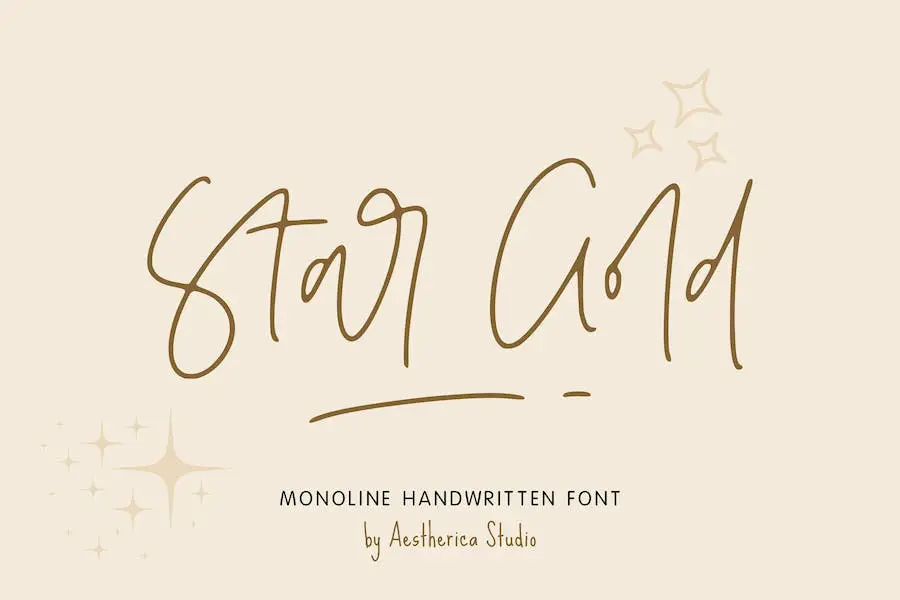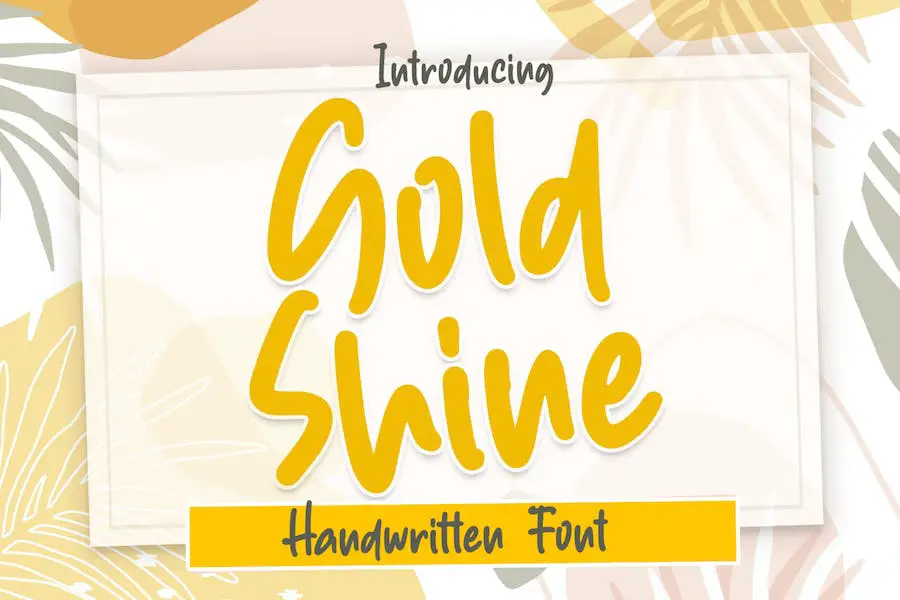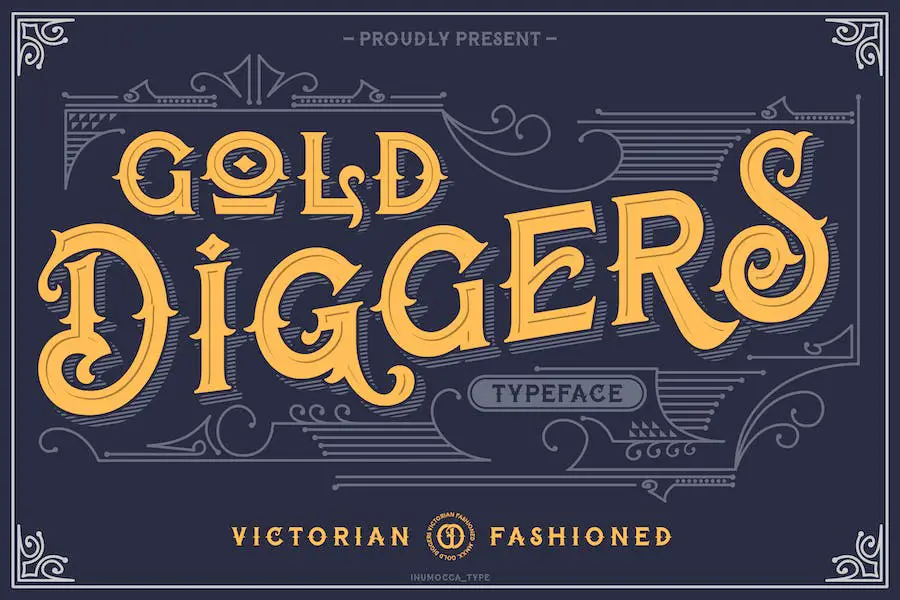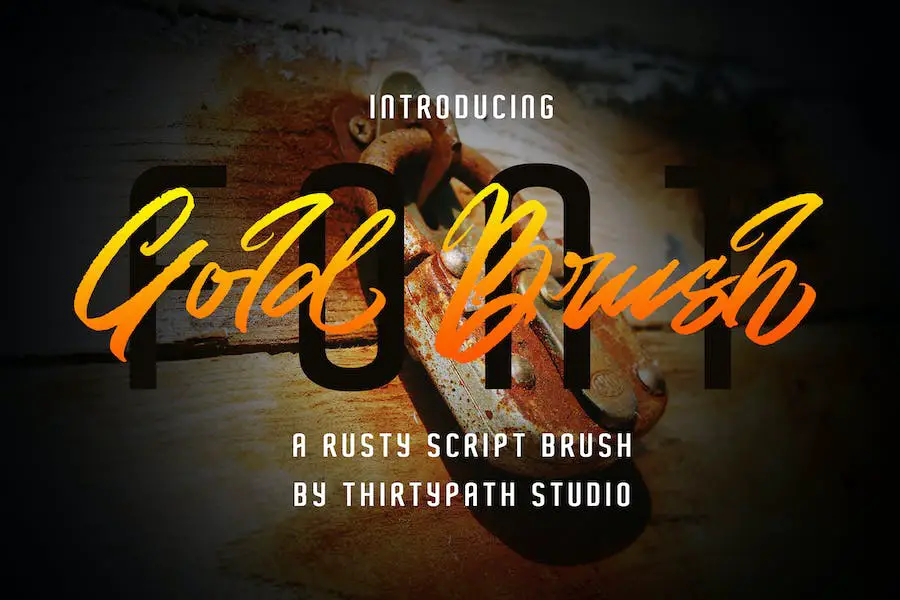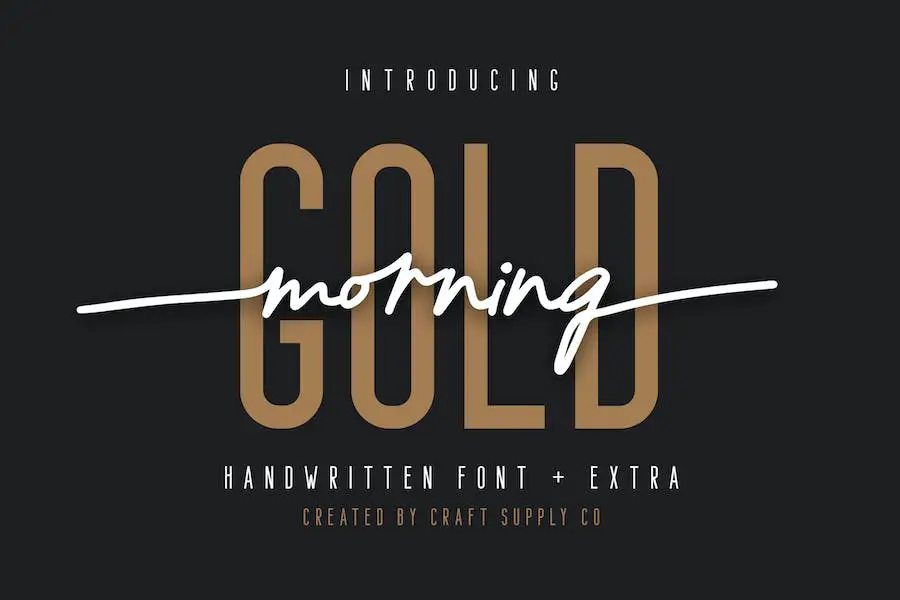
15 En İyi Altın Yazı Tipi 2023 (Ücretsiz ve Premium)
Yayınlanan: 2023-07-23Merhaba, sevgili grafik tasarımcılar! Projelerinizin tasarımını yükseltmek için mükemmel altın yazı tipinin peşinde misiniz? Doğru yere geldiniz. Bu blog gönderisinde, altın yazı tiplerinin dünyasına dalacağız ve size oradaki en iyi 15 yazı tipini sunacağız.
Şimdi, merak ediyor olabilirsiniz, neden altın yazı tipleri? Pekala, sana söyleyeyim. Altın yazı tipleri, herhangi bir tasarıma anında zarafet, telif hakkı ve incelik katabilir.
İster bir logo, ambalaj, davetiyeler veya hatta sadece bir sosyal medya gönderisi üzerinde çalışıyor olun, altın rengi bir yazı tipi kullanmak projenizi diğerlerinden farklı kılabilir.
Bu yazıda, şu anda trend olan en iyi 15 altın yazı tipini sergilemekle kalmayacak, aynı zamanda size her yazı tipi hakkında bazı ilginç istatistikler ve gerçekler sunacağız.
Bu nedenle, yalnızca görsel olarak çarpıcı olmakla kalmayan, aynı zamanda hedef kitleniz üzerinde kalıcı bir etki yaratmak için tasarlanmış yazı tiplerini keşfetmeye hazır olun. Altın yazı tiplerinin dünyasını birlikte keşfedelim ve keşfedelim!
En İyi Premium Altın Yazı Tipleri
Tasarım projelerinize zarafet ve çekicilik katmak mı istiyorsunuz? En iyi 15 premium altın yazı tipinden oluşan özenle seçilmiş seçkimizden başka bir yere bakmayın. Bu çarpıcı yazı tipleri, tasarımlarınızı bir sonraki seviyeye taşıyacak ve onlara lüks ve göz alıcı bir çekicilik kazandıracak.
Bu olmazsa olmaz altın yazı tipleriyle projelerinizi geliştirme fırsatını kaçırmayın - şimdi onları inceleyin ve tasarım oyununuzu yükseltin!
altın kızlar
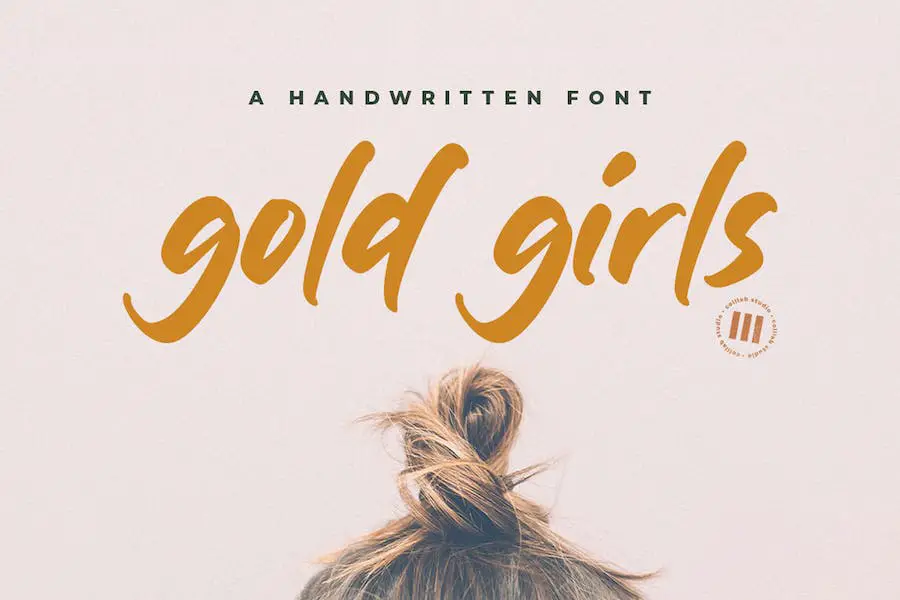
Gold Girls, herhangi bir projeye zarafet ve sofistike bir dokunuş katan süslü bir altın yazı tipidir. Modern yazı stili ve el yapımı kaligrafisi ile trend ve benzersiz bir seçim olarak öne çıkıyor.
Yazı tipi, tasarımlarınıza doğal ve akılda kalıcı bir görünüm kazandıran dekoratif karakterlere ve düzenli bir taban çizgisine sahiptir.
Davetiyeler, logolar veya sosyal medya grafikleri tasarlıyor olun, bu yazı tipi hedef kitlenizi etkileyecek kişiselleştirilmiş ve el yazısı bir dokunuş katacaktır.
saylena
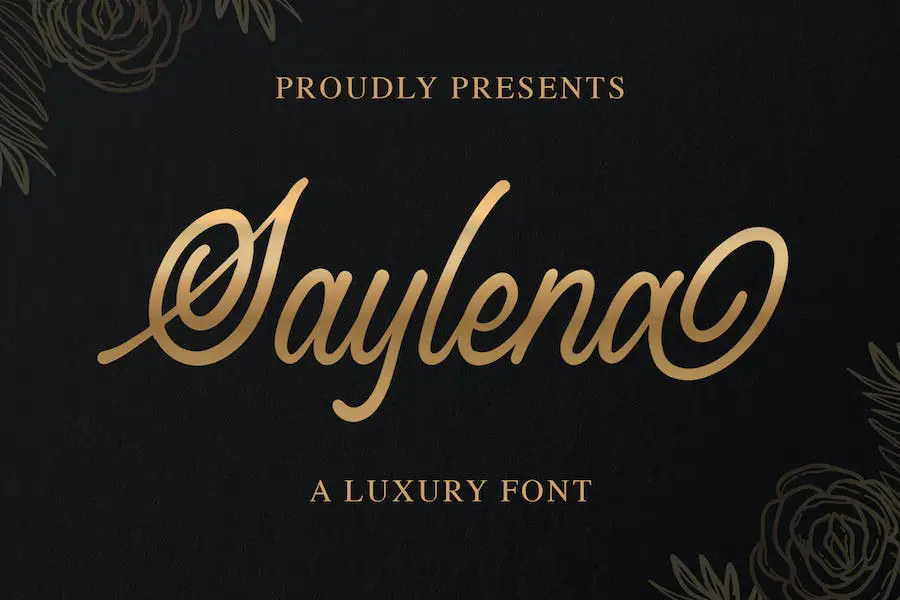
Saylena, projelerinin tasarımını geliştirmek isteyen grafik tasarımcılar için mükemmel olan çarpıcı bir Lüks Altın Yazı Tipidir.
Bu yazı tipi, lüks yazı stilinin zarafetinden ilham alarak imzalar, posterler, moda tasarımları, düğün davetiyeleri ve marka malzemeleri gibi çeşitli uygulamalar için idealdir.
Detaylara verdiği ince özen ve titiz işçiliği ile Saylena, benzersiz bir kalite seviyesi sunuyor. Kusursuz ve görsel olarak hoş bir sonuç sağlamak için her harf titizlikle hazırlanmıştır.
Yazı tipinin şık çizgileri ve incelikli eğrileri, ona gösterişli ve profesyonel bir görünüm vererek onu kaliteye ve hassasiyete değer veren tasarımcılar için mükemmel bir seçim haline getirir.
Anasayfa Altın
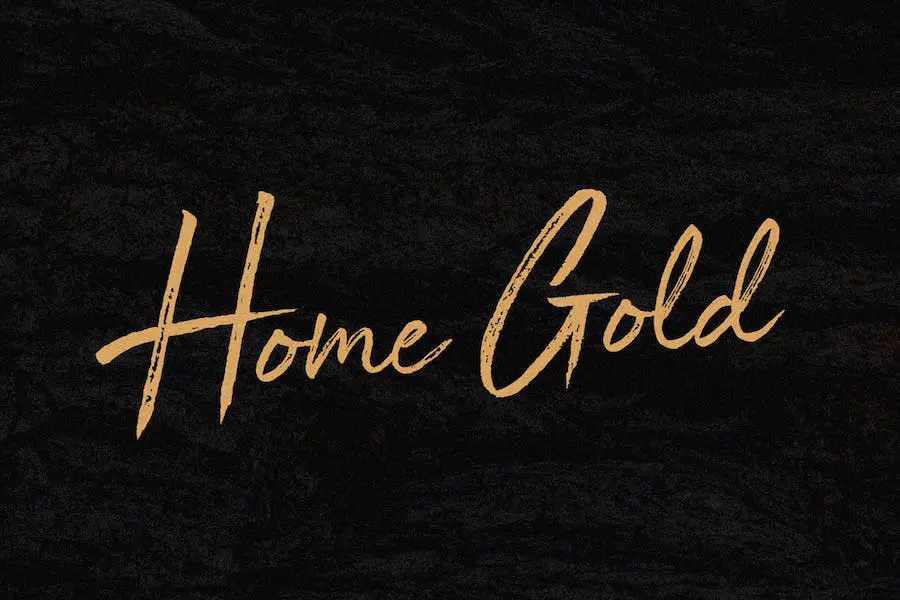
Tasarım projelerinizi geliştirmek için şık ve göz alıcı bir yazı tipi mi arıyorsunuz? Home Gold'dan başkasına bakmayın. Bu metalik altın yazı tipi, herhangi bir marka projesine, logoya, postere veya davetiyeye mükemmel bir ektir. Zarif ve lüks tasarımı ile kalıcı bir izlenim bırakacağından emin olabilirsiniz.
Home Gold yalnızca dijital tasarım dünyasında öne çıkmakla kalmaz, aynı zamanda ev dekorasyonuna da güzel bir şekilde katkıda bulunur. Bu çarpıcı altın yazı tipiyle kişiselleştirilmiş duvar sanatı veya dekoratif öğeler yarattığınızı hayal edin. Herhangi bir alanın stilini ve karmaşıklığını anında yükseltir.
Metalik altın tasarımı, herhangi bir projeye büyüleyici bir dokunuş katarak onu marka bilinci oluşturma, logolar, posterler, ev dekorasyonu, davetiyeler, bloglar, kartvizitler, ürün ambalajları ve çok daha fazlası için mükemmel kılar. Tasarım oyununuzu bugün Home Gold ile yükseltin.
Altın gül
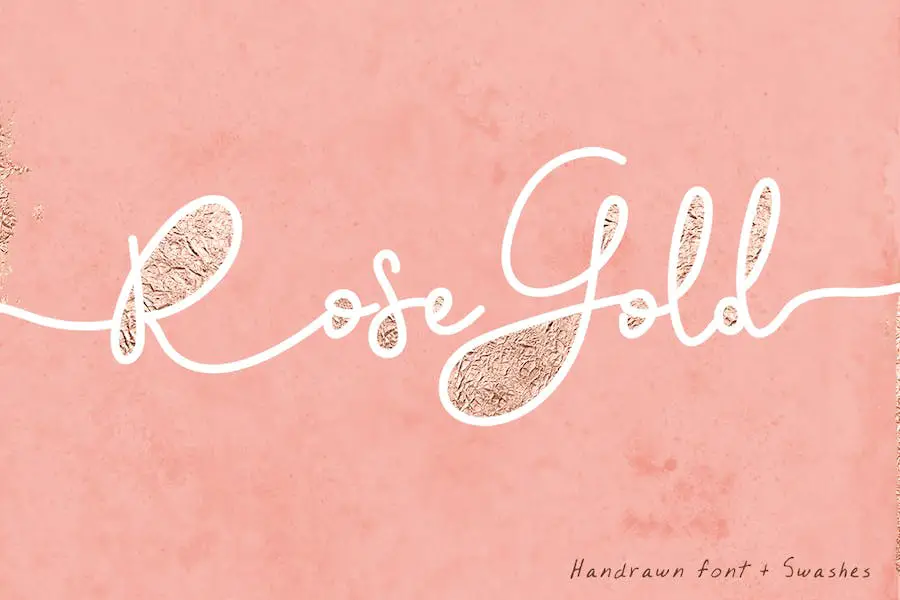
Rose Gold, herhangi bir tasarım projesini geliştiren süslü bir altın yazı tipidir. Pürüzsüz yazı stili posterlere, davetiyelere, tebrik kartlarına, kartvizitlere, logolara ve daha fazlasına zarafet ve incelik katar.
Dahil edilen 26 renk örneğiyle, güzel bir son dokunuş için yazı tipini istediğiniz estetikle kolayca eşleştirebilirsiniz.
İster projelerinizi yükseltmek isteyen bir grafik tasarımcı olun, ister sadece altın yazı tiplerinin güzelliğini takdir eden biri olun, Rose Gold yazı tipi koleksiyonunuza mutlaka sahip olmanız gereken bir eklentidir.
sonofon
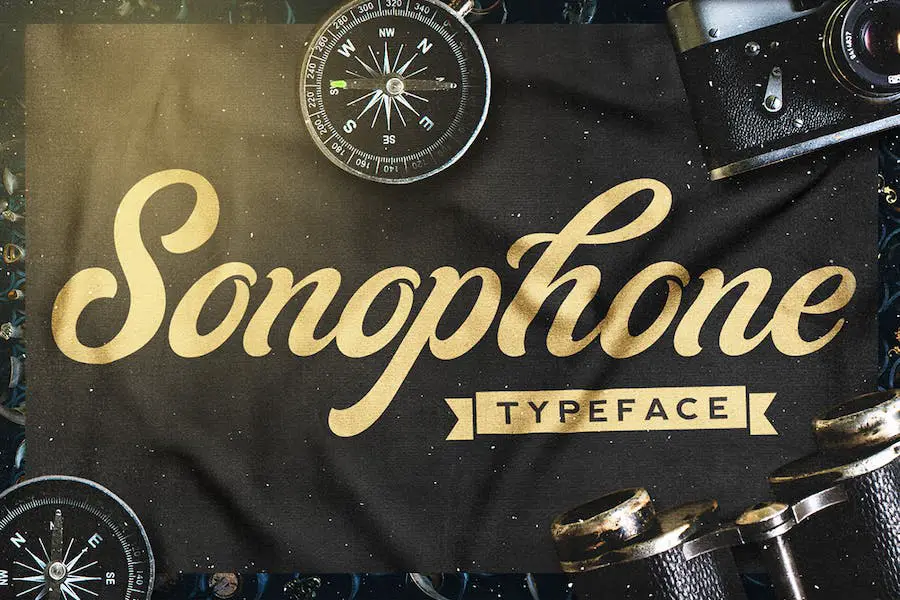
Sonophone, tipografi projelerinize nostaljik bir incelik katan, şaşırtıcı şekilde tasarlanmış bir Komut Dosyası Yazı Tipidir.
Güzel hazırlanmış glifleri ve benzersiz italik duruşuyla bu yazı tipi, logo tasarımı ve marka bilinci oluşturma için mükemmeldir. İster zarif davetiyeler, ister göz alıcı posterler oluşturuyor olun, Sonophone tasarımlarınızı bir sonraki seviyeye taşıyacak.
Zamansız zarafeti ve klasik çekiciliği, onu her grafik tasarımcı için olmazsa olmaz kılıyor. Dolayısıyla, projelerinize klas bir dokunuş katmak istiyorsanız, Sonophone'dan başkasına bakmayın.